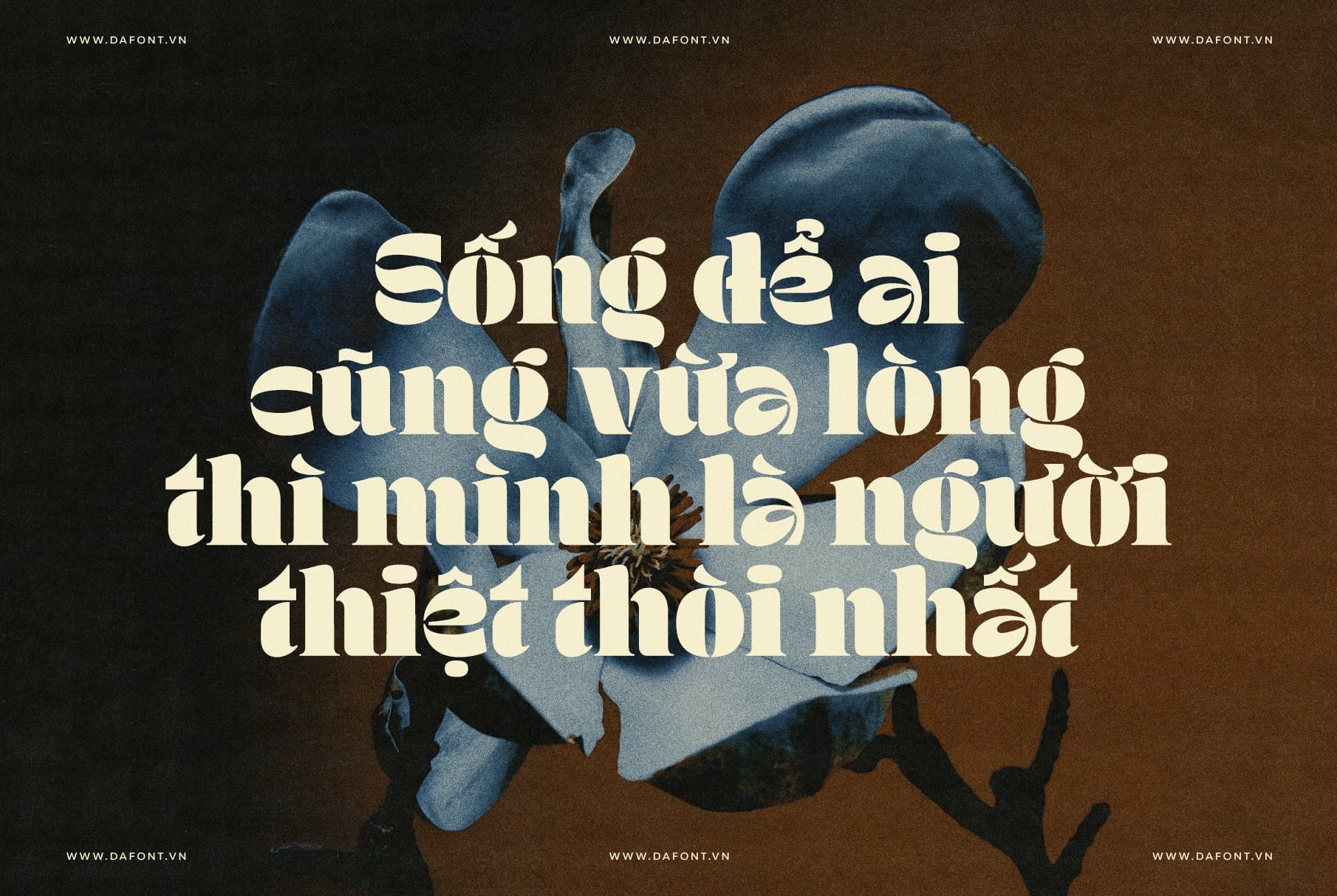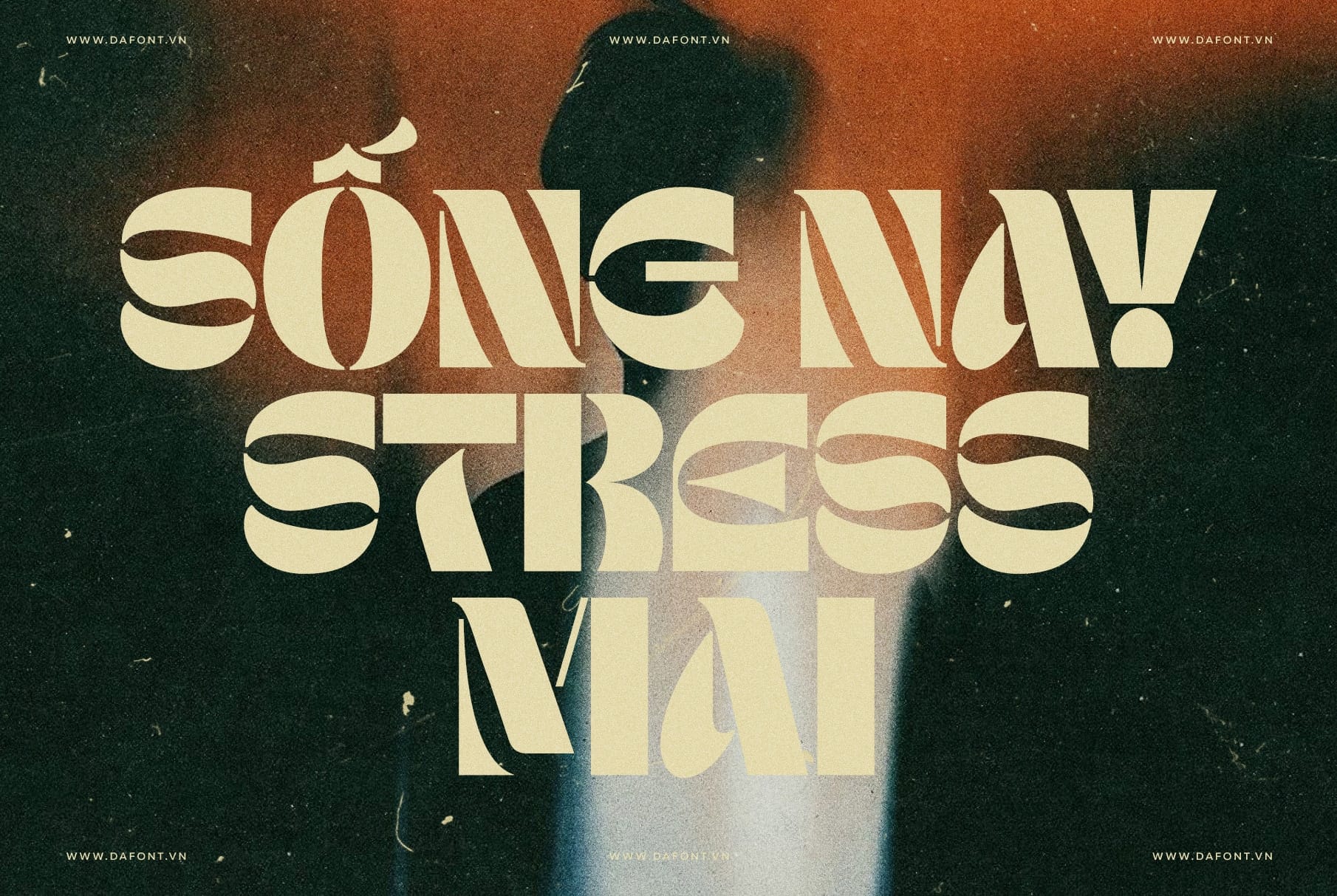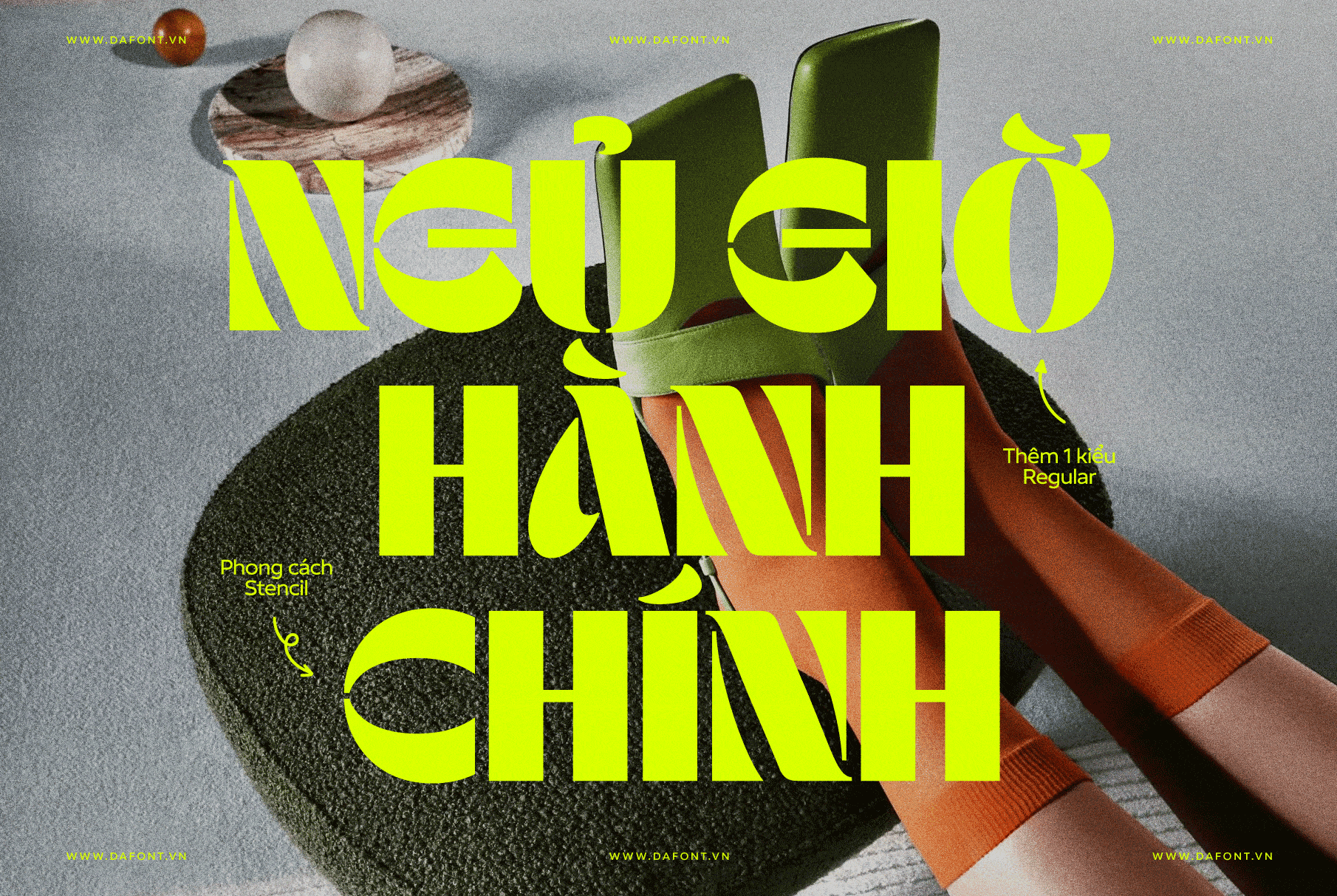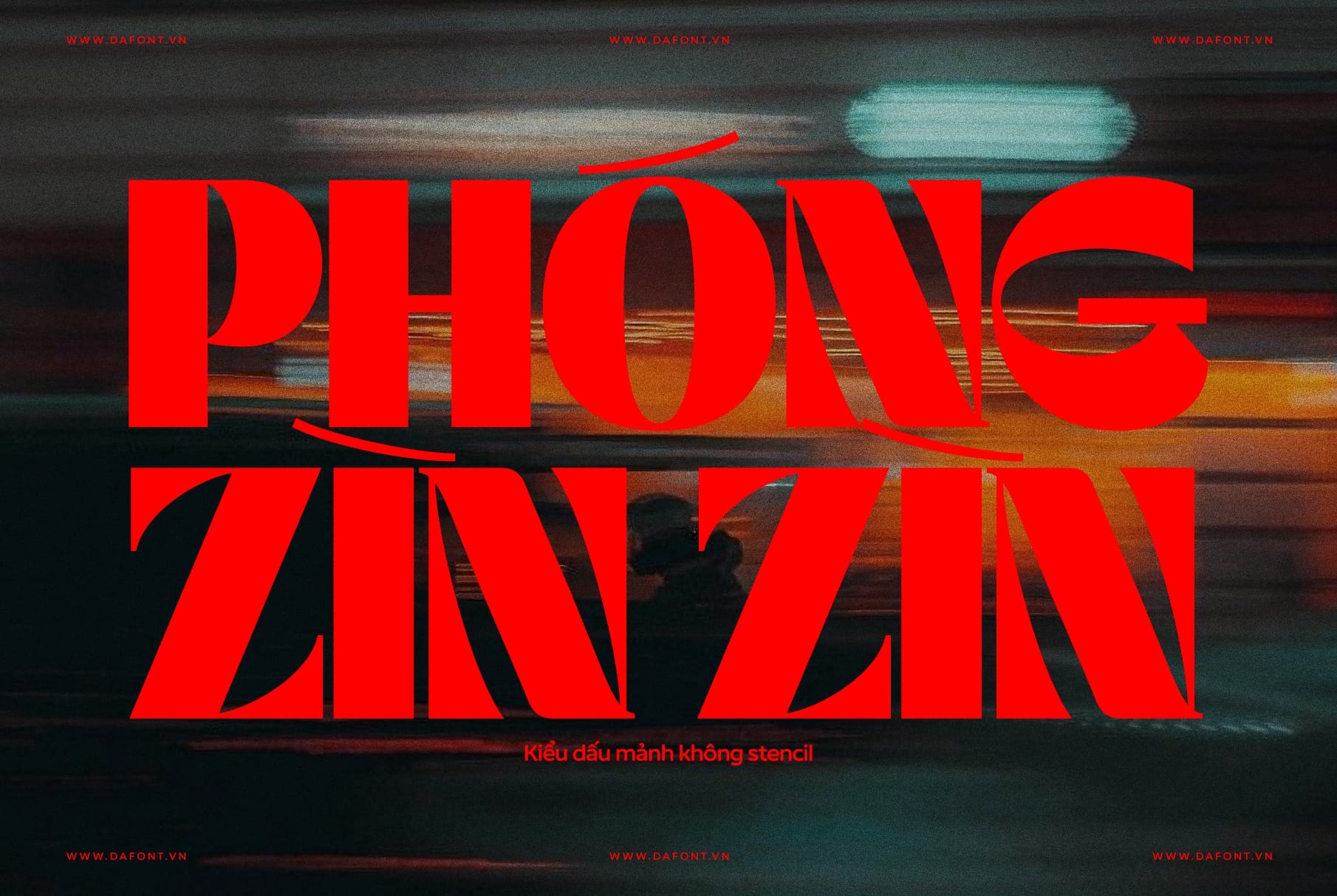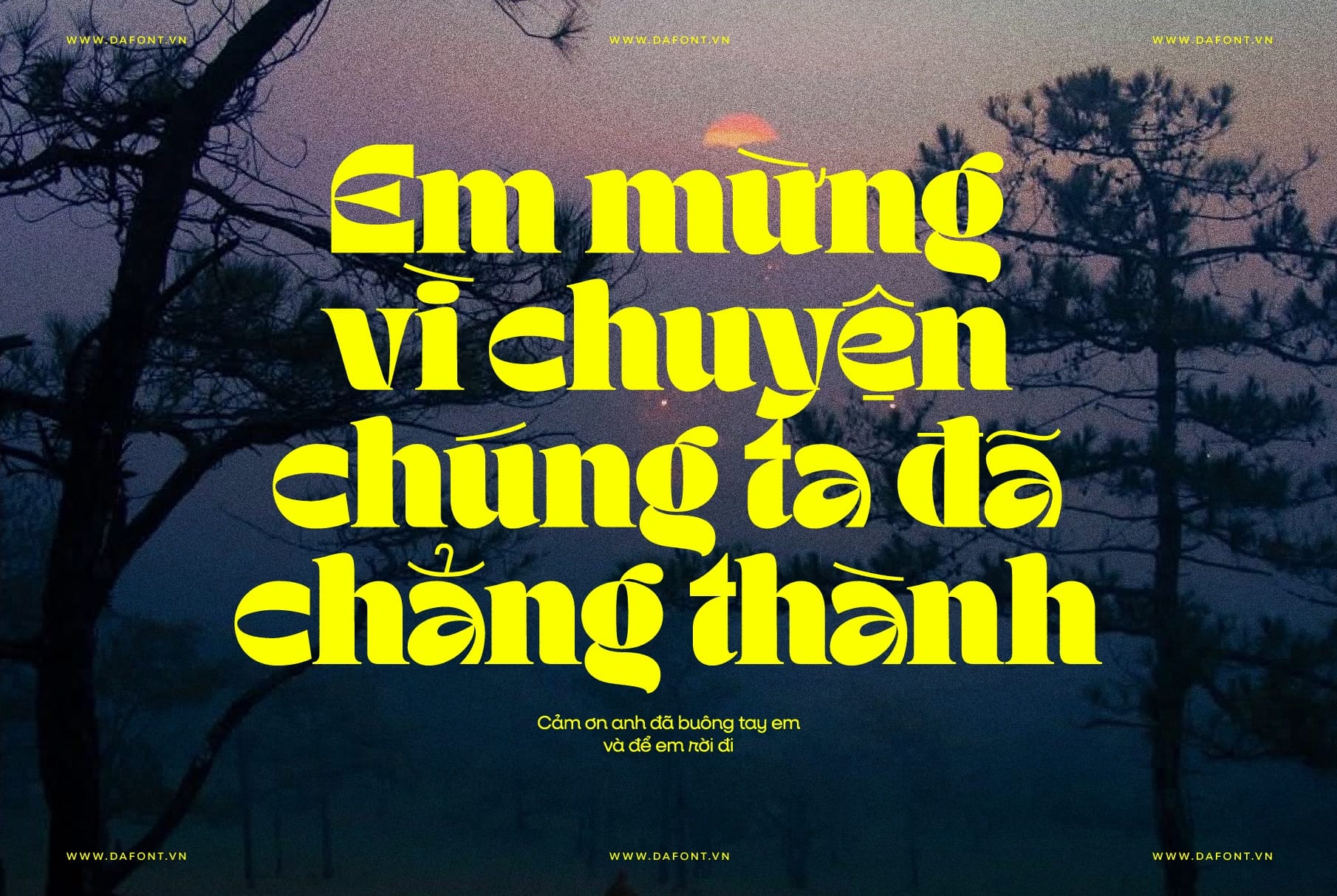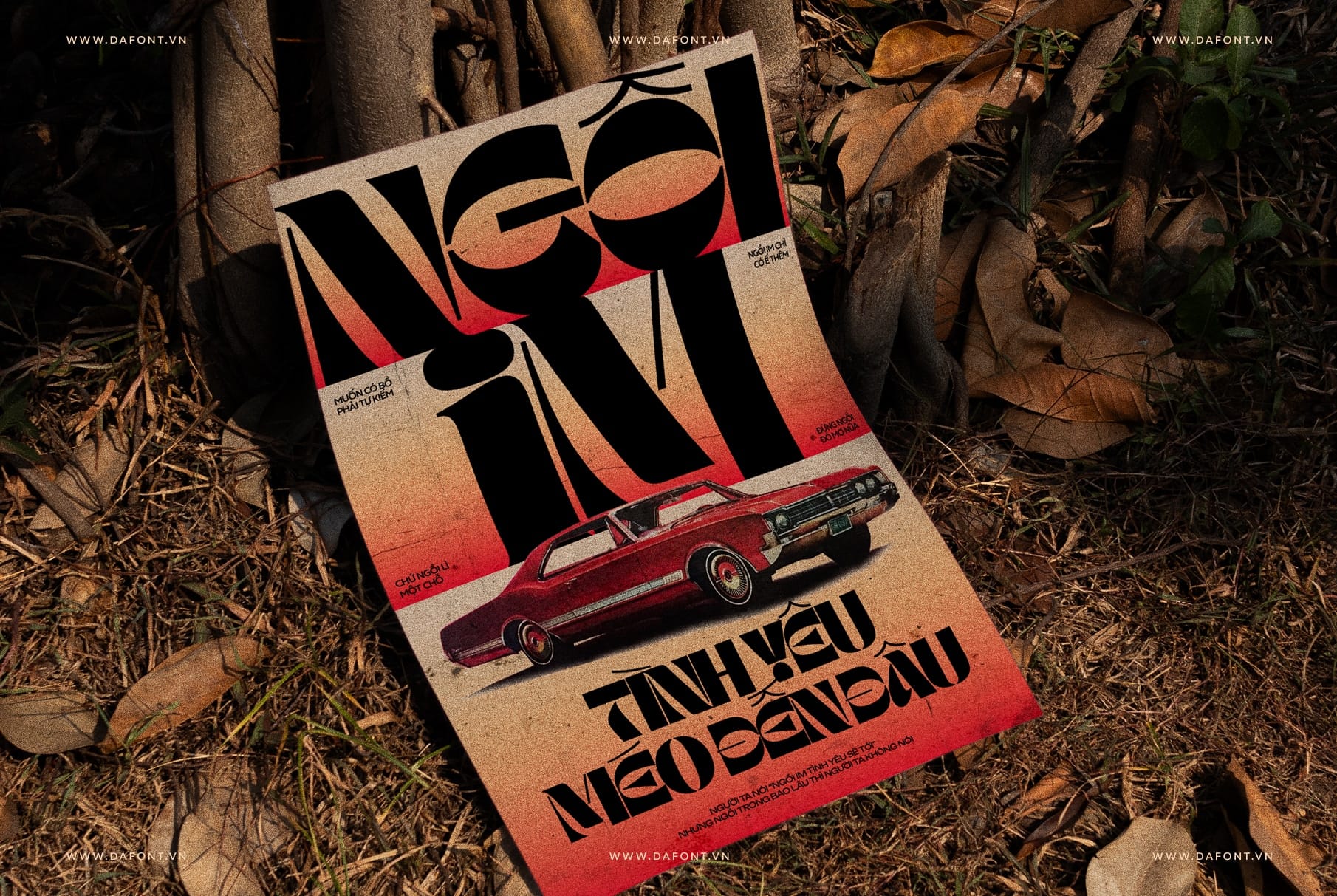
DFVN TAN – MISFITS
Font stencil retro đậm chất nổi loạn và táo báo
DFVN TAN – MISFITS là một font display stencil mang đậm chất retro, với các nét chữ dày, đậm và những khoảng “đứt nét” đặc trưng giúp tạo nên cảm giác nổi loạn, phá cách nhưng vẫn rất có chủ ý. Font được thiết kế để trở thành điểm nhấn thị giác mạnh mẽ trong layout, đặc biệt phù hợp với các thiết kế mang tinh thần cá tính, nổi bật, hơi “bất cần” nhưng vẫn giữ được tính thẩm mỹ.
Đặc điểm nổi bật của DFVN TAN – MISFITS
Điểm khiến TAN – MISFITS khác biệt so với các display retro thông thường nằm ở cấu trúc stencil: các nét bị “cắt khúc” một cách nghệ thuật, tạo cảm giác công nghiệp – poster – signage rất rõ rệt. Kết hợp với form chữ dày, đậm và tỷ lệ vui mắt, font mang lại cảm giác mạnh mẽ, phóng khoáng nhưng không bị thô.
• Font display stencil retro: nét đứt có chủ ý, gợi liên tưởng poster in, biển bảng, signage cổ điển.
• Nét chữ dày, đậm, cấu trúc vững, dễ đọc ở kích thước lớn, rất hợp với tiêu đề, logo, chữ chính trên poster.
• Phong cách phóng khoáng, phá cách nhưng vẫn giữ được tính cân đối, giúp font vừa cá tính vừa không “khó dùng”.
• Tổng thể mang mood & tone: mạnh mẽ, sinh động, retro cá tính – có thể dùng cho nhiều phong cách từ vintage đến hiện đại.
DFVN TAN – MISFITS – Bản Việt hóa chất lượng
DFVN TAN – MISFITS được Việt hóa hoàn chỉnh, tinh chỉnh kỹ lưỡng để hỗ trợ tiếng Việt có dấu một cách ổn định, đẹp mắt. Bản Việt hóa không chỉ thêm dấu mà còn tối ưu kerning và phát triển thêm vài biến thể để tăng khả năng ứng dụng trong thiết kế.
Những điểm đáng chú ý:
• Việt hóa đầy đủ, bổ sung dấu cho toàn bộ ký tự, đảm bảo các chữ tiếng Việt hiển thị đồng đều, không lệch.
• Kerning được tinh chỉnh kỹ cho các cặp ký tự có dấu, giúp đàn chữ tiếng Việt trông cân đối và dễ đọc hơn.
Có 2 bộ dấu riêng biệt:
• Bộ dấu mặc định: nét dày, đồng bộ với cấu trúc stencil retro, cho cảm giác mạnh mẽ, chắc nịch.
• Bộ dấu thanh mảnh: nét mỏng, cao và thoáng hơn, tạo cảm giác tinh tế, mới lạ nhưng vẫn hài hòa với thân chữ.
Ngoài ra, DFVN bổ sung thêm phiên bản không stencil (không đứt nét) để người dùng có thêm lựa chọn khi cần sự liền mạch, gọn gàng hơn. Mọi lựa chọn (bộ dấu, bản stencil/không stencil) có thể thao tác dễ dàng qua tính năng OpenType trong các phần mềm có hỗ trợ.
Nhờ những nâng cấp này, DFVN TAN – MISFITS trở nên linh hoạt hơn rất nhiều, phù hợp với nhiều loại thiết kế khác nhau.
Tổng kết
Với sự pha trộn hoàn hảo giữa nét hoài cổ của phong cách stencil và sự phá cách, vui nhộn trong từng đường nét, DFVN TAN – MISFITS Việt hóa xứng đáng là font chữ không thể bỏ qua. Sự linh hoạt tuyệt vời từ hai bộ dấu tiếng Việt được tinh chỉnh kỹ lưỡng càng làm tăng thêm giá trị thực tiễn và tính ứng dụng cao cho kiểu chữ này.